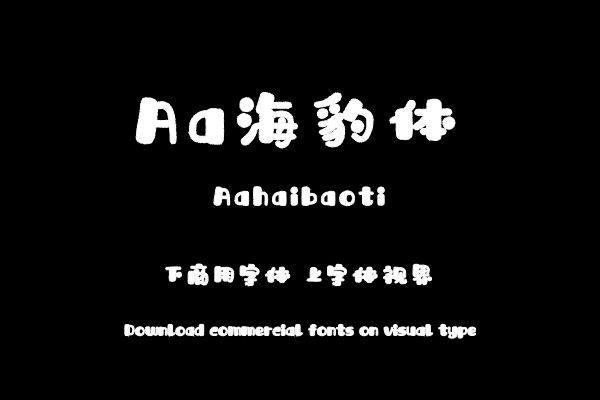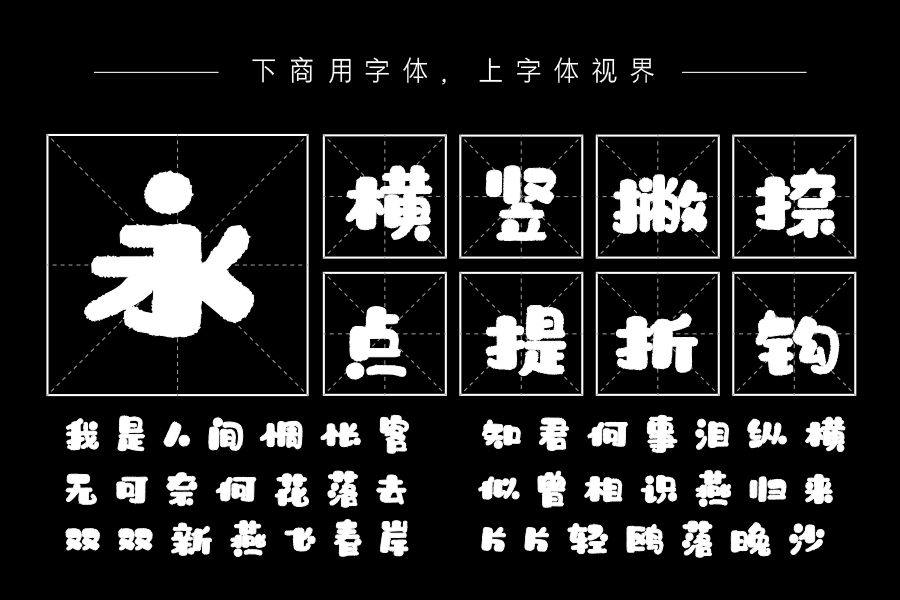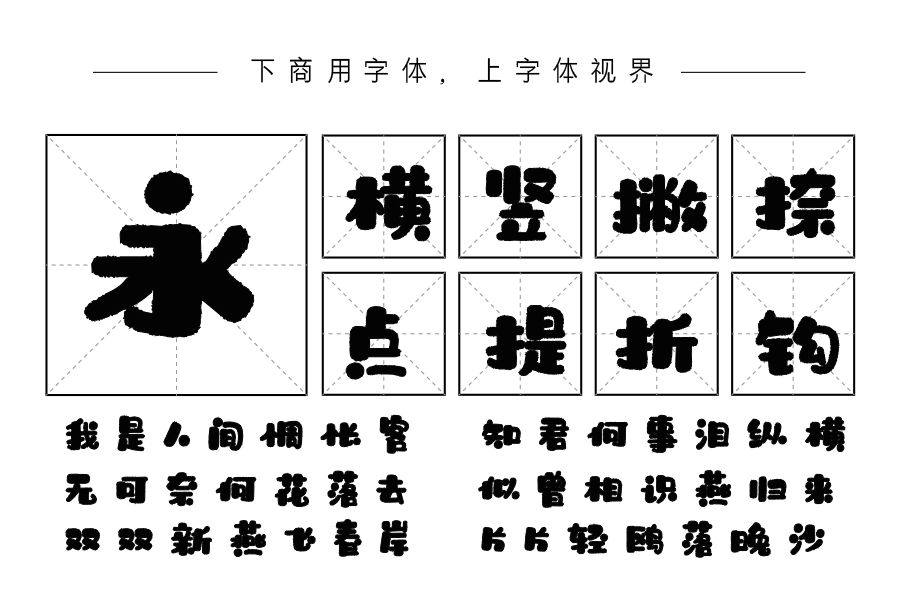
笔画圆润Q弹,俏皮可爱,字形结构变化多样,粗细对比强烈,富有节奏感。购买须知:“下载服务费”与“字体VIP”所获得字体 仅用于个人非商用, 商用请联系付费授权。本字体为电脑用字,手机没有root权限不支持直接手机换字(手机如何root,请自行百度搜索教程)。购买前请先 了解清楚后再付款 ,字体为虚拟产品无法回收 一旦购买不支持退款。